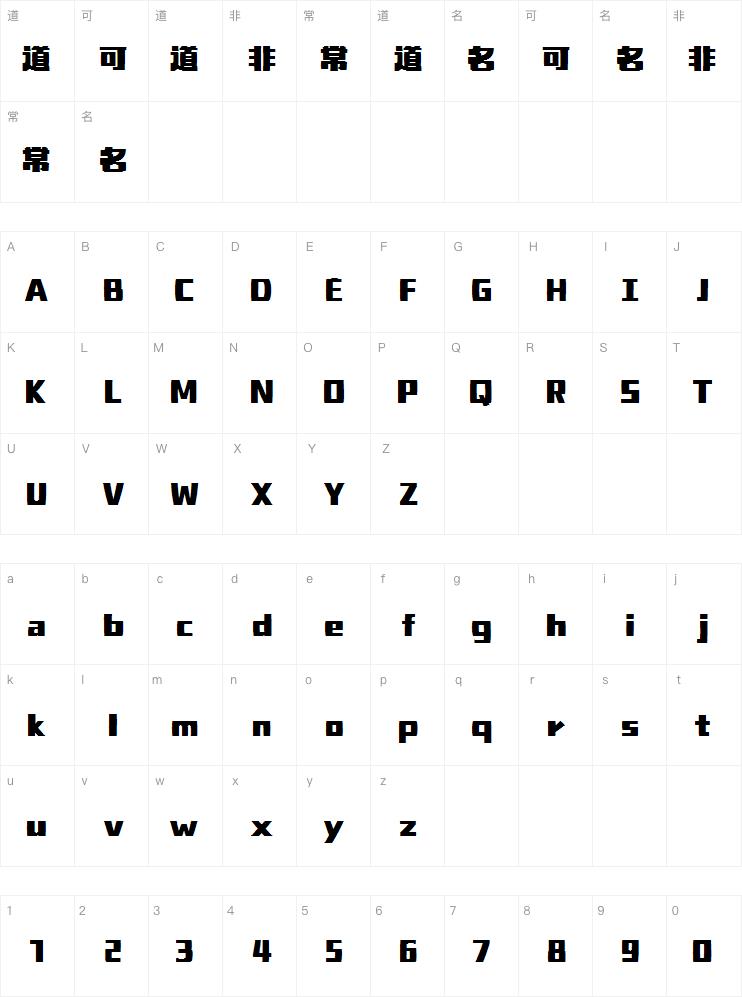
山海方糖黑w
山海方糖黑,是一款全新的字体,包含汉字9169个,符号200+个。该字体是一款综艺黑体字体,是一款具有强劲视觉冲击力的综艺风格标题字体。字形充实填满整个字框,左右略宽,造型兼具硬朗和柔和。直线与圆弧的笔画构成坚实有力,拥有宽大的中宫、粗厚且直线化的笔画设计、简洁明了的笔画切角,带来强有力的视觉冲击效果。该字体在综艺黑体的基础上做了诸多创新,结构区别于传统黑体的规规矩矩,增加俏皮性和随意性,使得该字体既有着端肃的凝重,又有着流动的美感。在正式用字场合落落大方,在日常使用环境中不失亲切友好,能够在保留综艺黑体基本特征的基础上更能适应当下时尚潮流的需要,助力各大新产品夺取标题主战场。